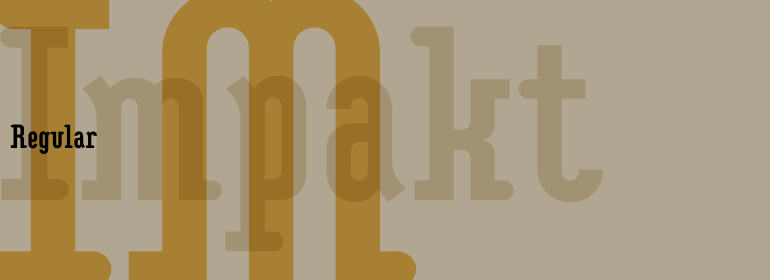
Impakt™
Impakt™,这款字体结构工整、笔画清晰,兼顾美观与易读性,适用于标题、正文、海报、包装、LOGO 等多种场景。字形优雅稳定,风格百搭耐看,适配日常排版与创意设计,让文字呈现更舒适、更具质感。Impakt™一笔一画,皆是细节,以均衡的比例、流畅的线条打造舒适视觉体验,字形端正大气,风格简约现代。无论是商业设计、品牌宣传还是日常排版,都能轻松驾驭,让文字更有格调与力量。Impakt™字体下载。